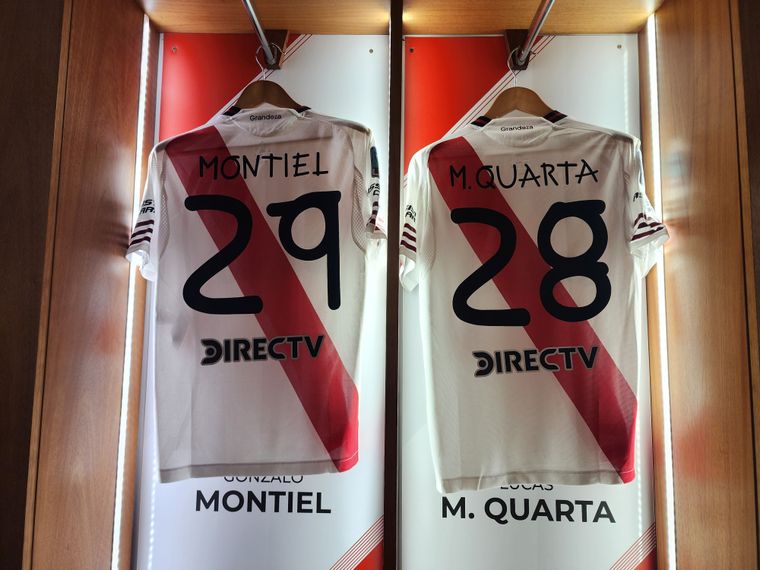
El motivo por el que River usó una tipografía especial en la camiseta en el partido ante Sarmiento
River saltó a la cancha con una camiseta diferente a la habitual para enfrentar a Sarmiento de Junín en el Monumental.
River lució una tipografía especial en su camiseta.
@RiverPlateRiver Plate enfrentó este domingo en el Monumental a Sarmiento de Junín por la fecha 11 del Torneo Apertura. Ambos equipos saltaron a la cancha con sus indumentarias titulares, pero el cuadro de Núñez utilizó una camiseta con una leve pero bien visible diferencia.
En la espalda, la Banda lució en los números y nombres de los jugadores una tipografía notoriamente distinta a la habitual, que aparenta haber sido dibujada a mano, y que se enmarca en una importante campaña global de visibilidad e inclusión.
River usó una camiseta especial por el Día Mundial del Síndrome de Down
El motivo detrás de esta movida es el Día Mundial del Síndrome de Down, que se celebra anualmente todos los 21 de marzo desde el 2006 y que es reconocido por la ONU desde diciembre de 2011. El Millonario se sumó a etsa conmemoración y aprovechó el partido más cercano a la fecha en el que jugara como local.
La tipografía fue creada en 2012 por la artista catalana con síndrome de Down Anna Vives, y desde entonces se ha convertido en un símbolo para la visibilidad de las personas con esta condición genética. La diseñadora fue invitada al Monumental durante la última semana y posó con una camiseta con su nombre y el número 21.
Es la segunda vez que River se suma a esta campaña. La primera había sido en 2013, oportunidad en la que la propia artista le entregó una camiseta a Ramón Díaz, DT por aquel entonces. Solo otros siete equipos han utilizado estos números en partidos oficiales en el resto del mundo: Barcelona (España), Porto (Portugal), Universidad Católica (Chile), Corinthians (Brasil), América (México), Dinamo Kiev (Ucrania) y Kaizer Chiefs (Sudáfrica).